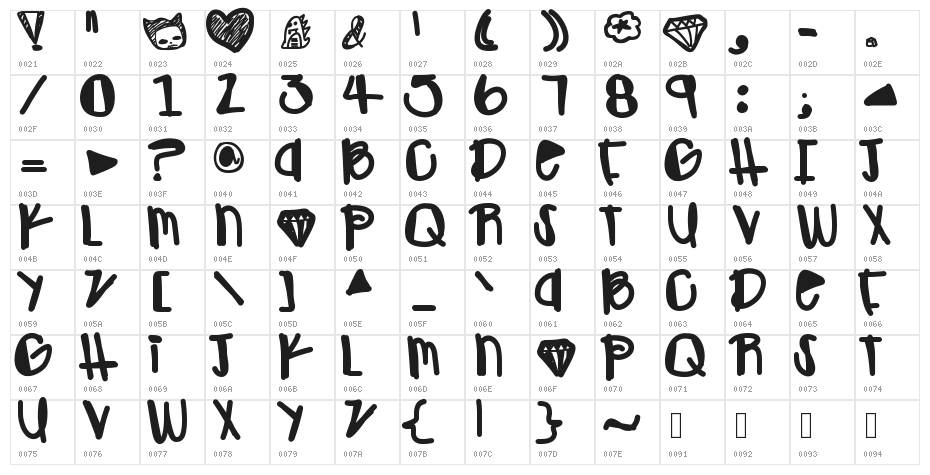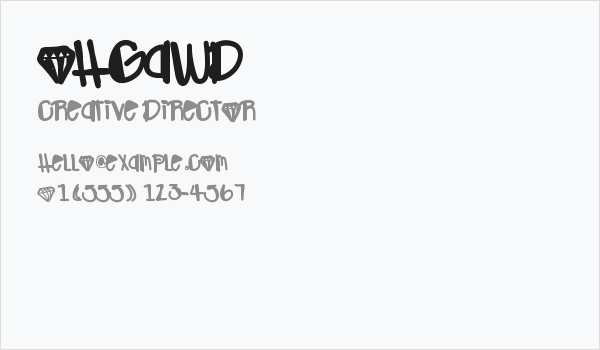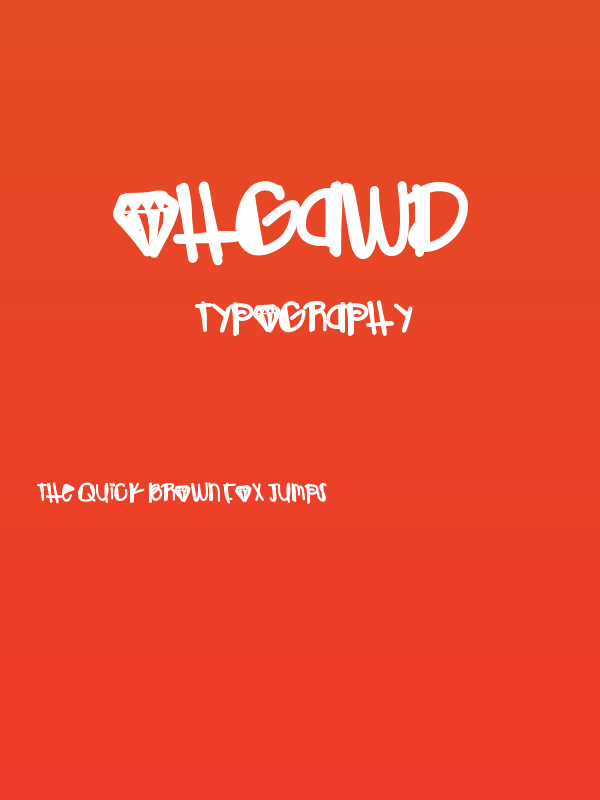
OhGawd Font
| Stil general | Playful and Creative |
| Proiecte propuse | Ideal for children's books, party invitations, playful branding, and creative posters. |